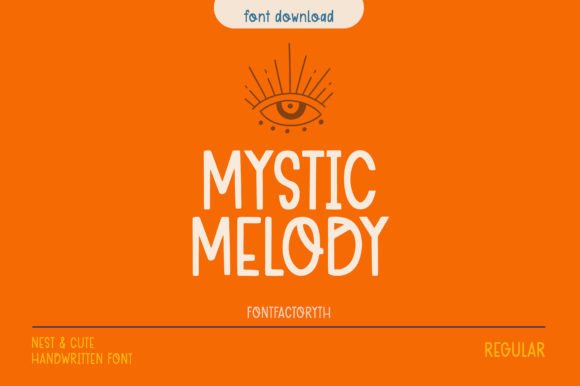
Mystic Melody Font
Пошук відповідних елементів дизайну може бути складним, але Mystic Melody Font пропонує виняткову колекцію, яка миттєво покращить вашу роботу.
Незалежно від того, чи створюєте ви продукти POD (друк на вимогу), весільні запрошення або графіку для соціальних мереж, Mystic Melody Font стане ідеальним вибором.
Порада експерта: комбінуйте ці елементи з доповнюючими шрифтами, щоб створювати унікальні, привабливі дизайни, що виділяються на ринку.